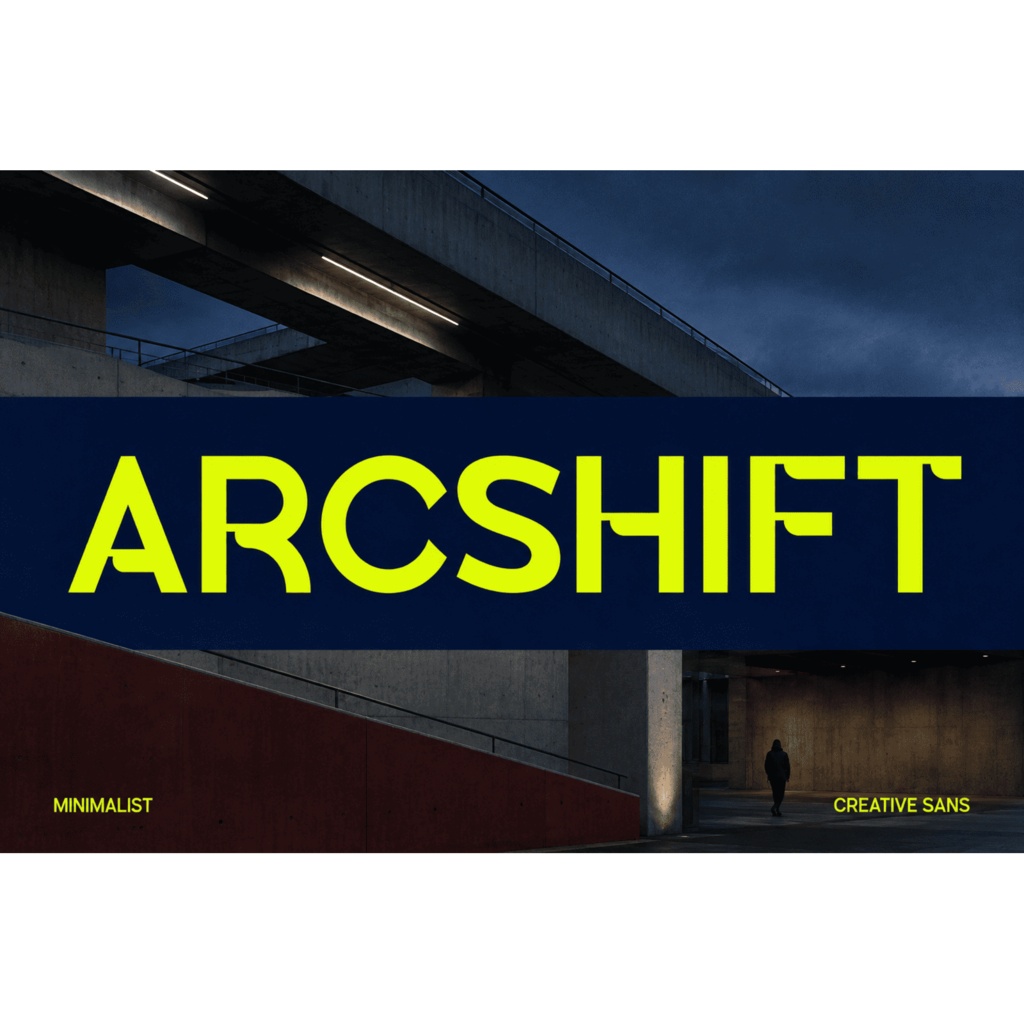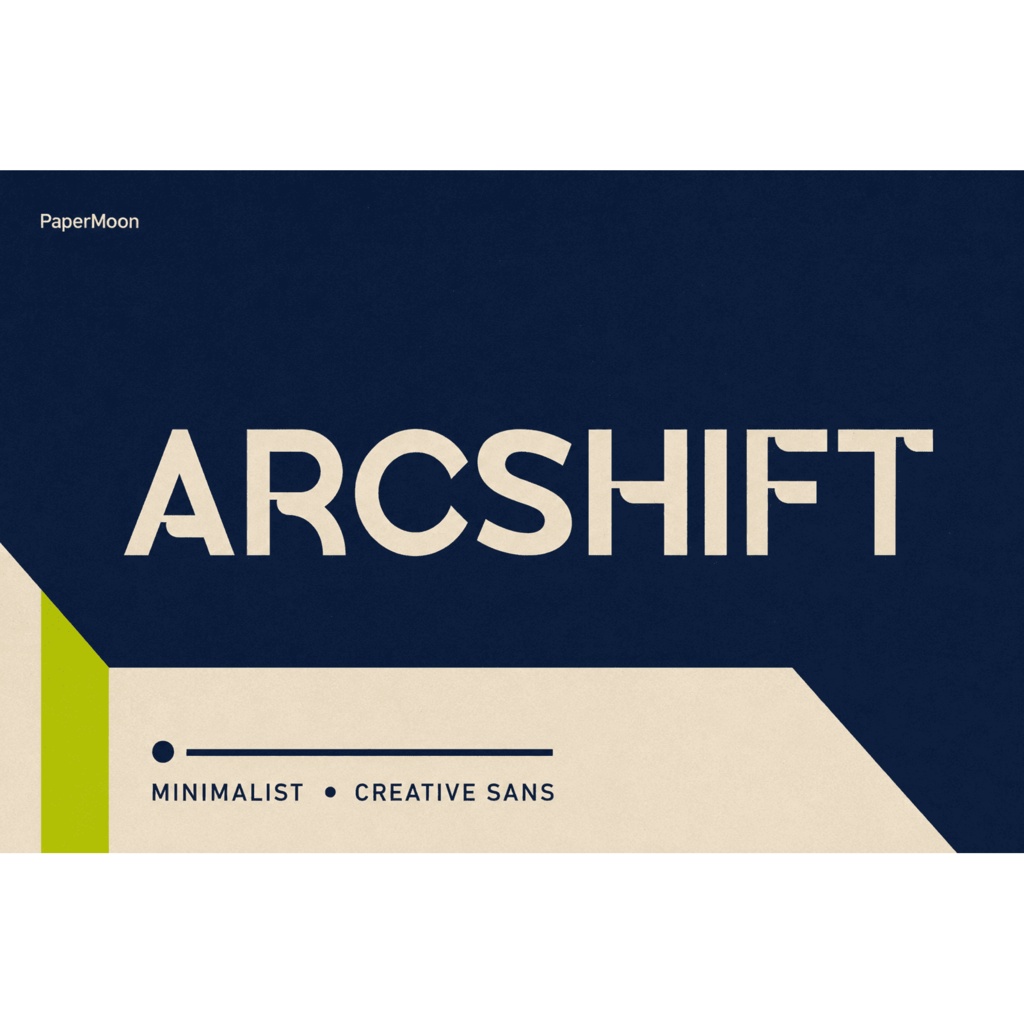
Arcshift | モダンサンセリフ欧文フォント | ロゴ・WEB・ブランディング向け
Arcshift(アークシフト)は、クリーンでミニマルなモダンサンセリフの欧文(ラテン文字)フォントです。直線的で整ったプロポーションの Regular と、前方へ動きを出す Italic の2スタイルを収録し、ロゴ・ブランディング・WEB・エディトリアル・ポスターなど幅広いクリエイティブで使える一組です。 収録内容 / Included ・Arcshift Regular: OTF / TTF / WOFF / WOFF2 ・Arcshift Italic: OTF / TTF / WOFF / WOFF2 ・計8ファイル(2スタイル × 4形式 / 8 files total) 対応文字 / Character Set ・Basic Latin(アルファベット大・小文字、数字、約物)と Latin-1 の文字・アクセントに対応 ・各スタイル 170グリフ / 171マッピング文字(UPM 1000) ・ひらがな・カタカナ・漢字、キリル文字、ギリシャ文字は未収録です(Latin only、日本語非対応) 用途 / Uses ・ロゴ・サイン・ブランドロゴ ・ブランディング・コーポレート資料 ・WEB・UI・アプリ ・ポスター・チラシ・パッケージ・見出し ・映像・SNSグラフィック・ディスプレイ用途 ・Regular は安定した見出し・本文に、Italic は強調や方向性のある表現に 形式 / Formats ・OTF(OpenType)/ TTF(TrueType)/ WOFF / WOFF2 の4形式 ・OpenType 機能: 標準合字(liga)・カーニング(kern)に対応 ・スタイリスティックオルタネートは非搭載です 対応環境 / Compatibility ・Windows / macOS に対応。OTF・TTF は Adobe Photoshop / Illustrator / InDesign、Microsoft Word、Canva、Procreate、Figma、Affinity 各アプリ、Cricut Design Space、Silhouette Studio など、インストールして使えるアプリで利用可能 ・WOFF / WOFF2 は CSS の @font-face でWebフォントとして利用可能